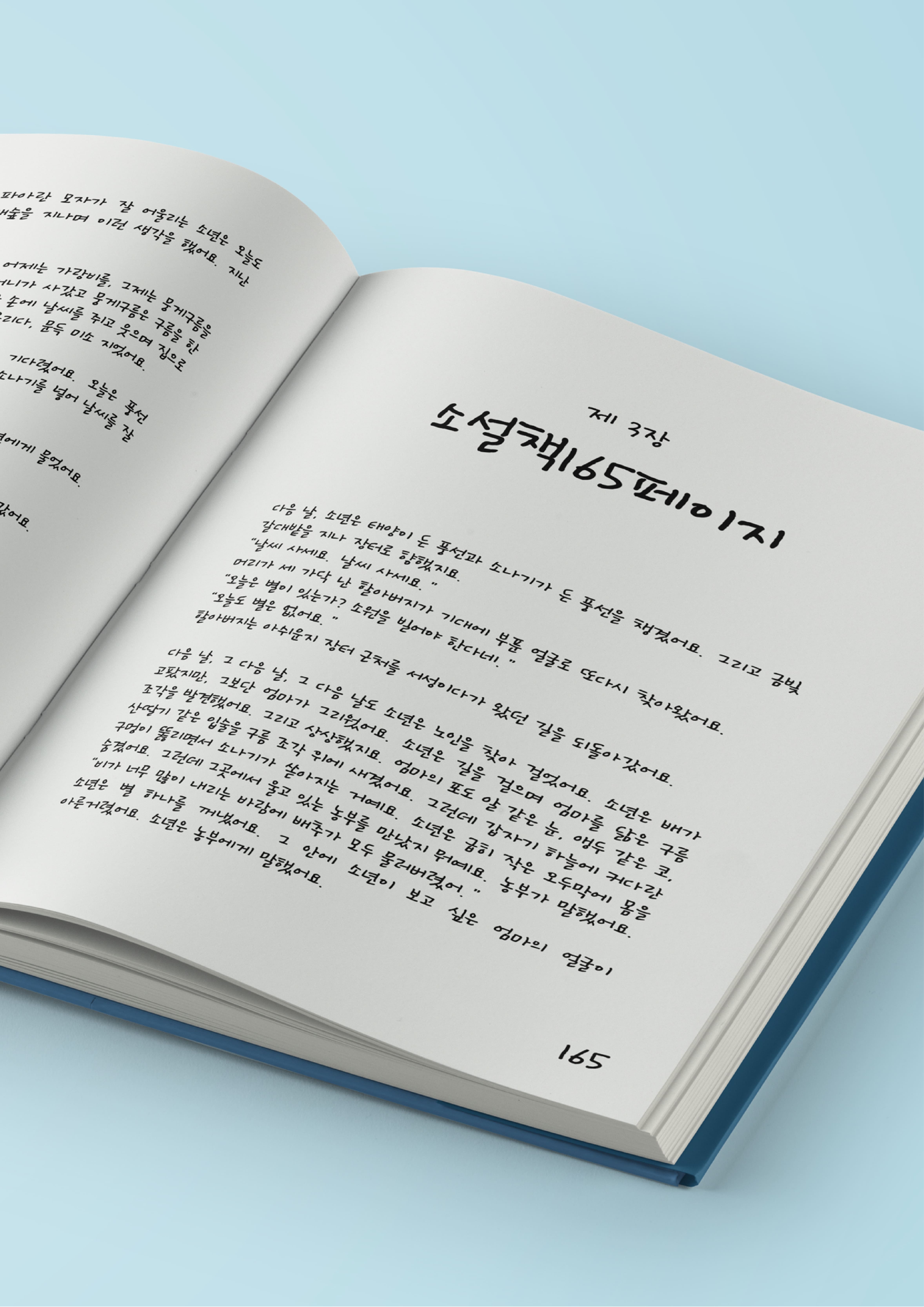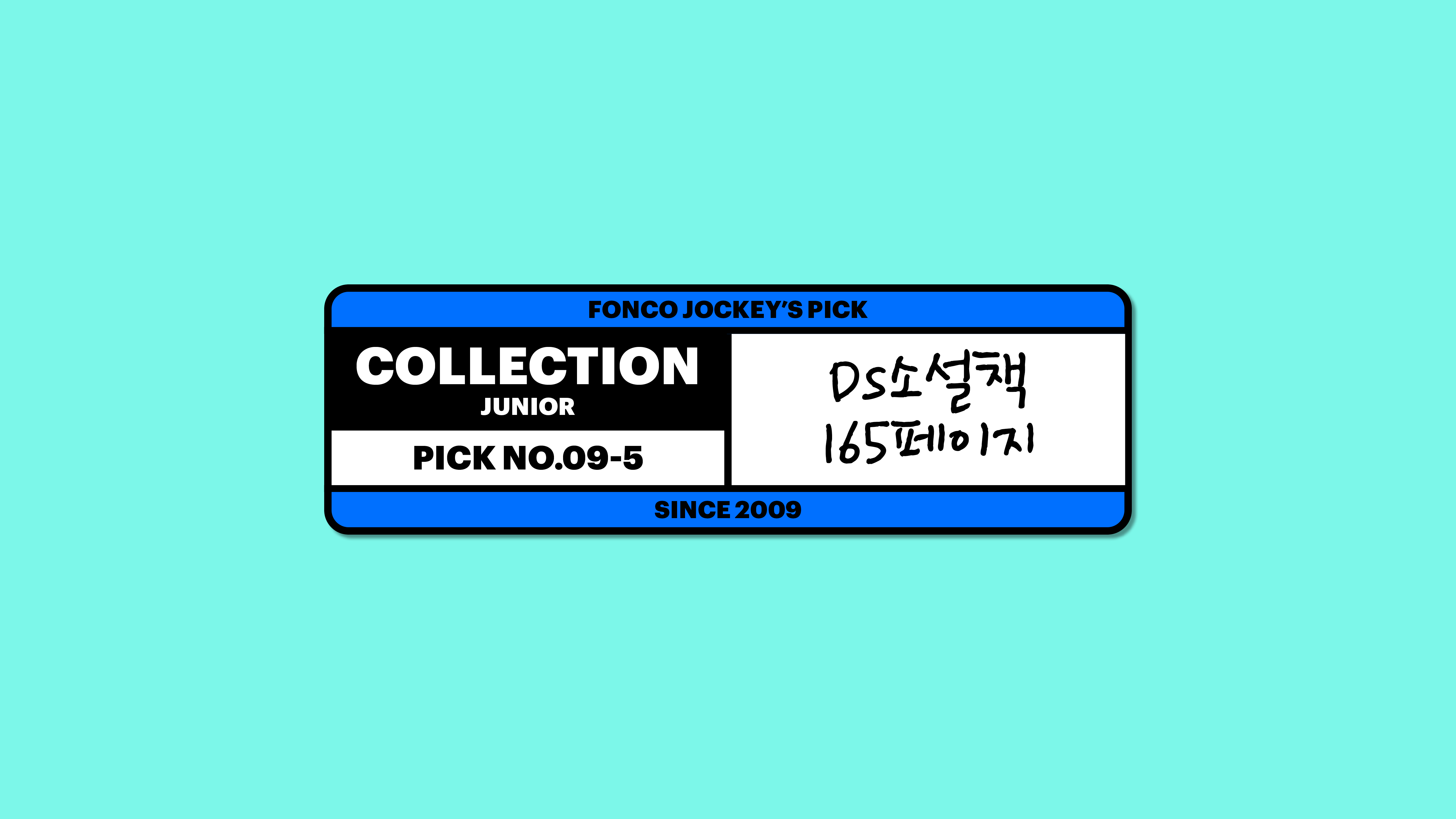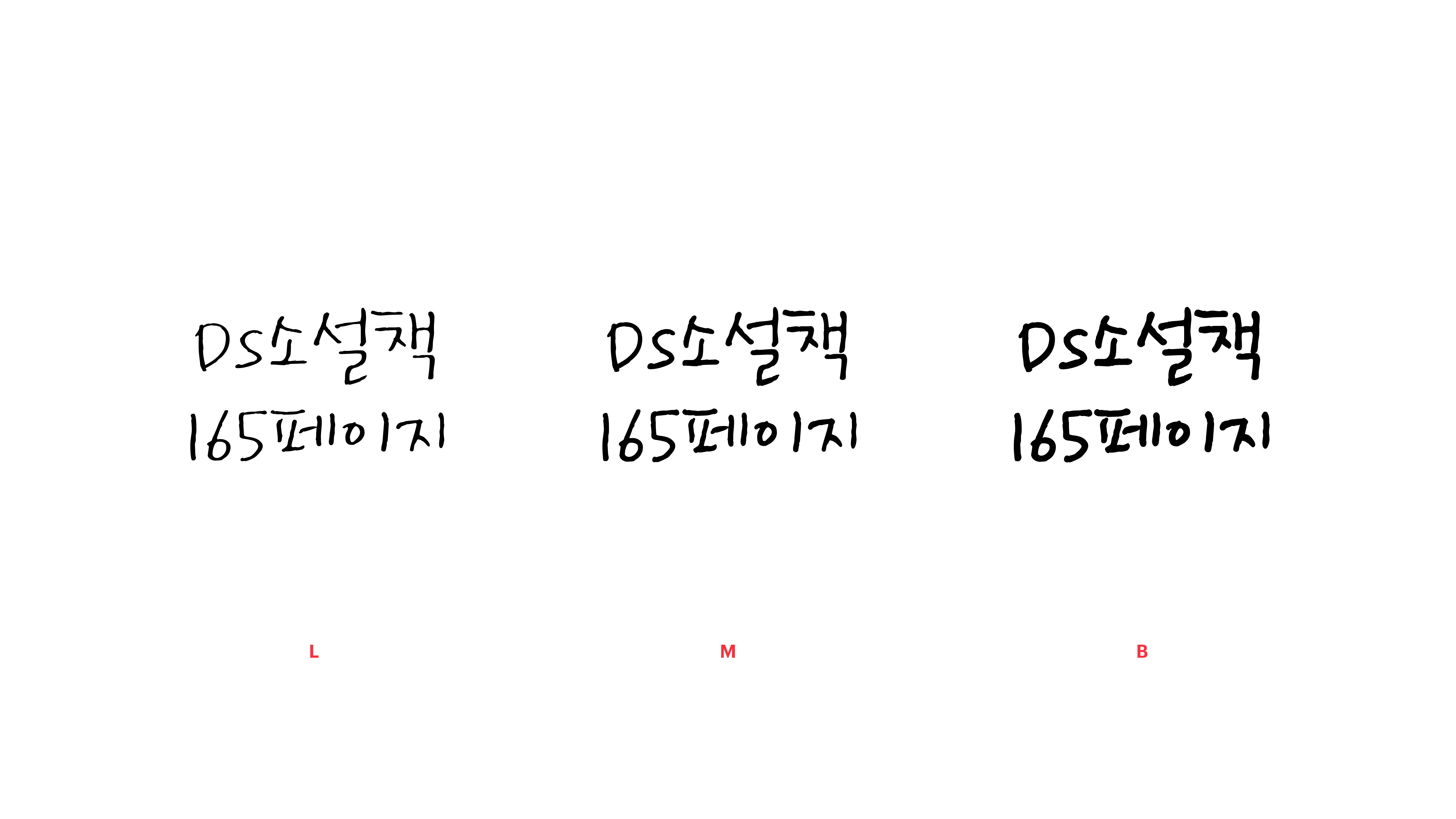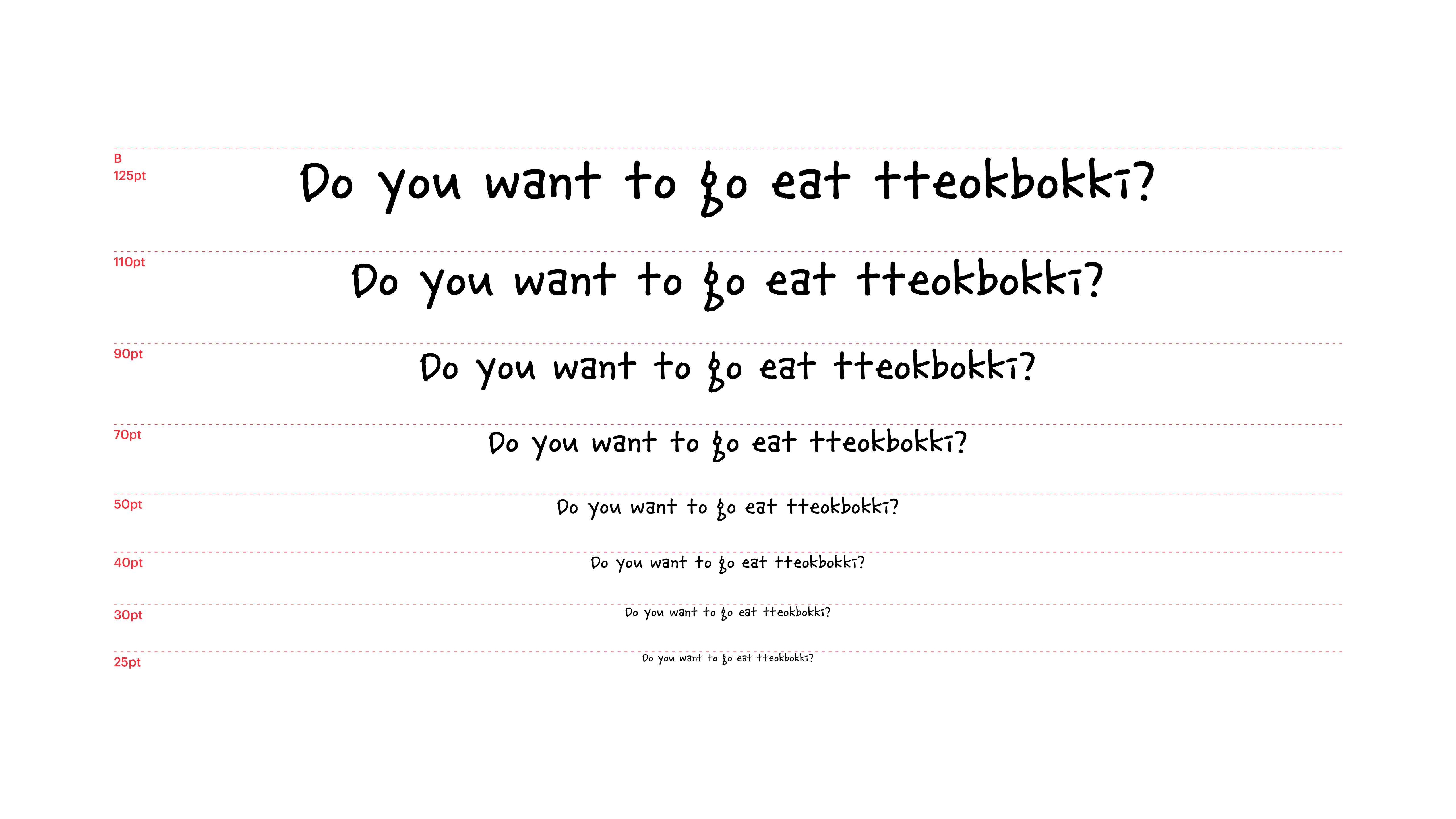
그 친구가 소설책 165페이지에 끼워서 전해준 비밀 쪽지에는 어떤 이야기가 적혀 있을까요? 미묘한 떨림을 간직한 손글씨 폰트의 섬세한 획이 핑크빛 기대를 품게 합니다. ‘사랑해’보다는 ‘좋아해’에, ‘좋아해’보다는 ‘좋아하는 것 같아’에 더 어울리는 수줍은 폰트. 하지만 ‘떡볶이 먹으러 갈래?’ 같은 애매한 제안이 적혀 있으면 어떡하죠? 아무래도 제가 더 많이 좋아하는 것 같은데.
Yoon DS소설책165페이지